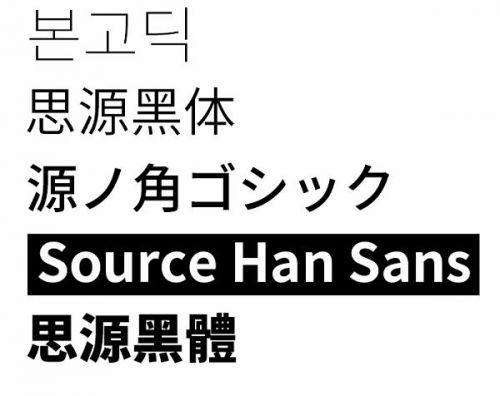
6年前 Adobe宣布与谷歌合作推出开源字体“思源黑体”(Source Han San),将适用于中文、日文、韩文,可以免除开发者和设计师获取不同字体授权的时间。
据悉,思源黑体有七种字体粗细(ExtraLight、Light、Normal、Regular、Medium、Bold 和 Heavy),完全支持日文、韩文、繁体中文和简体中文,还包括来自 Source Sans字体家族的拉丁文、希腊文和西里尔文字形。
一直以来,开发者要为网站、应用程序显示中文、日文、韩文,必须要获得不同字体的授权,才能在作品中准确传递内容给用户,而获取授权过程冗长费时,效率也比较低。
Adobe方面介绍称,思源黑体是第一款在同一字体系列中支持不同语言及区域性差异的开源字体,涵盖15亿人口地区。
据报道,考虑到地域性差异,Adobe和谷歌等合作伙伴为每种字体开发了65535种字型,开发耗时3年多,集结了100多人的团队。